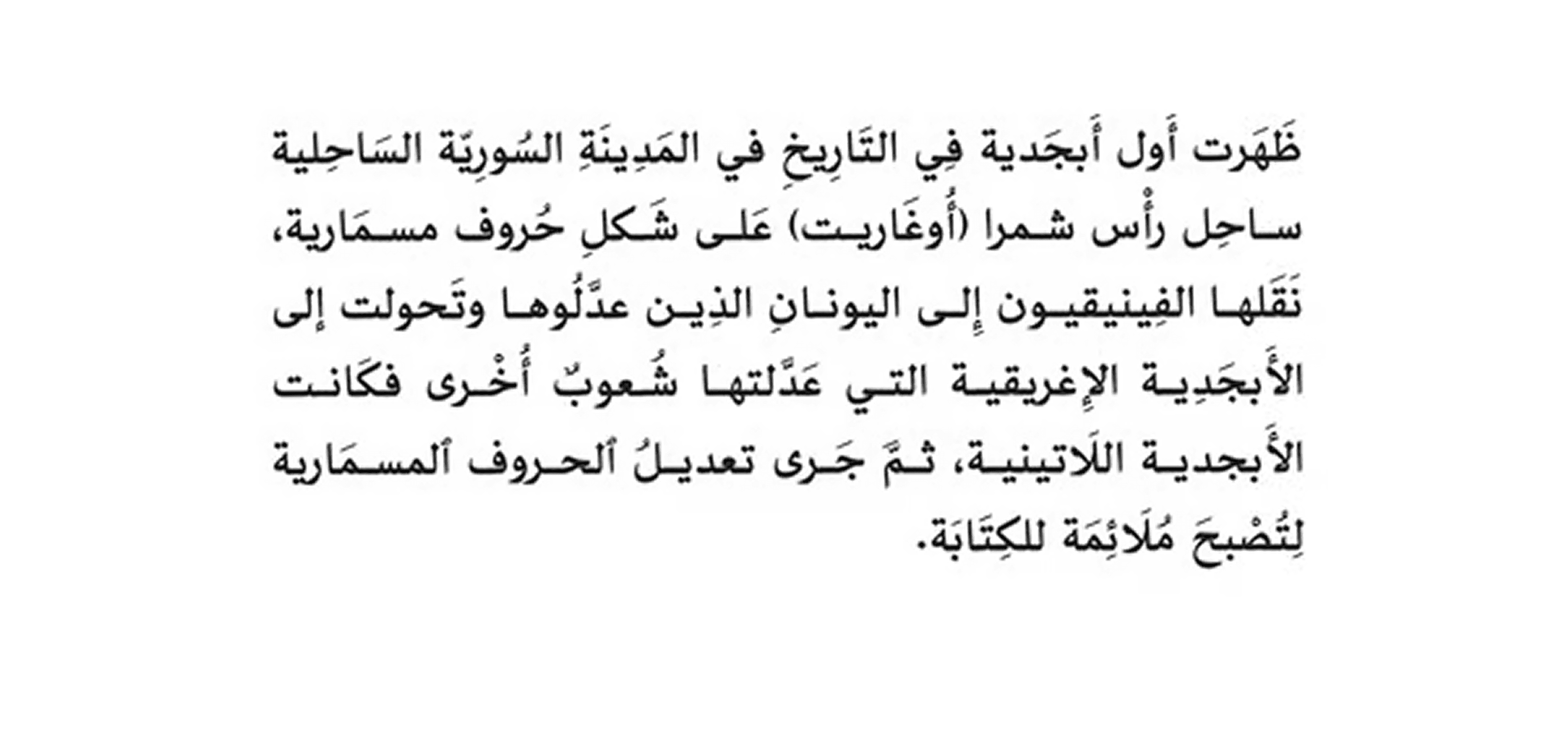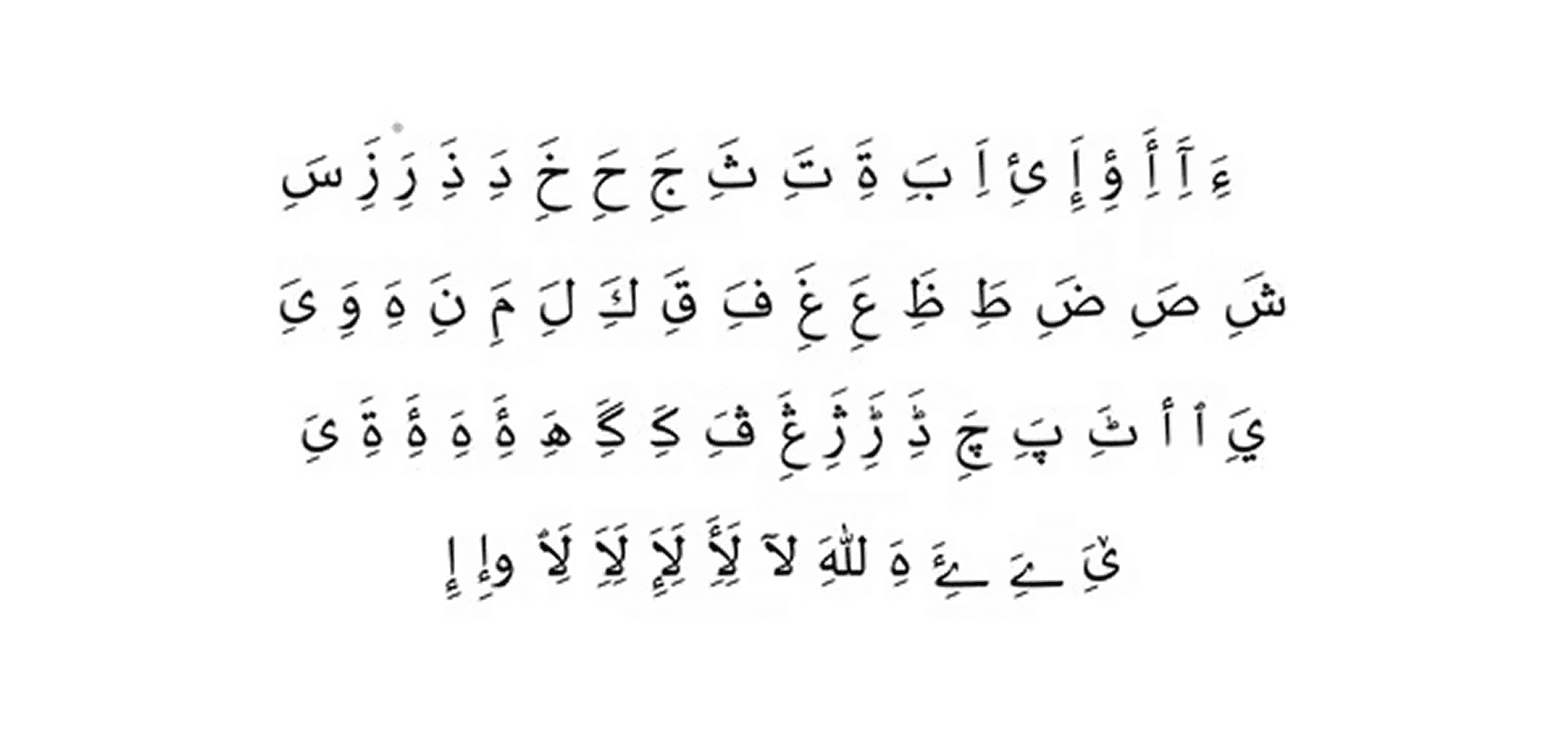
الخط JH Lina هو خط عربي من نوع النسخ، ويتضمن أربعة أوزان. يُعد مناسبًا للنصوص الطويلة، العناوين، الهوية البصرية، النشرات الإخبارية، المجلات، اللافتات، والنشر الإلكتروني...
تم ضبط مواضع التشكيل بدقة لتلبية متطلبات الناشرين.